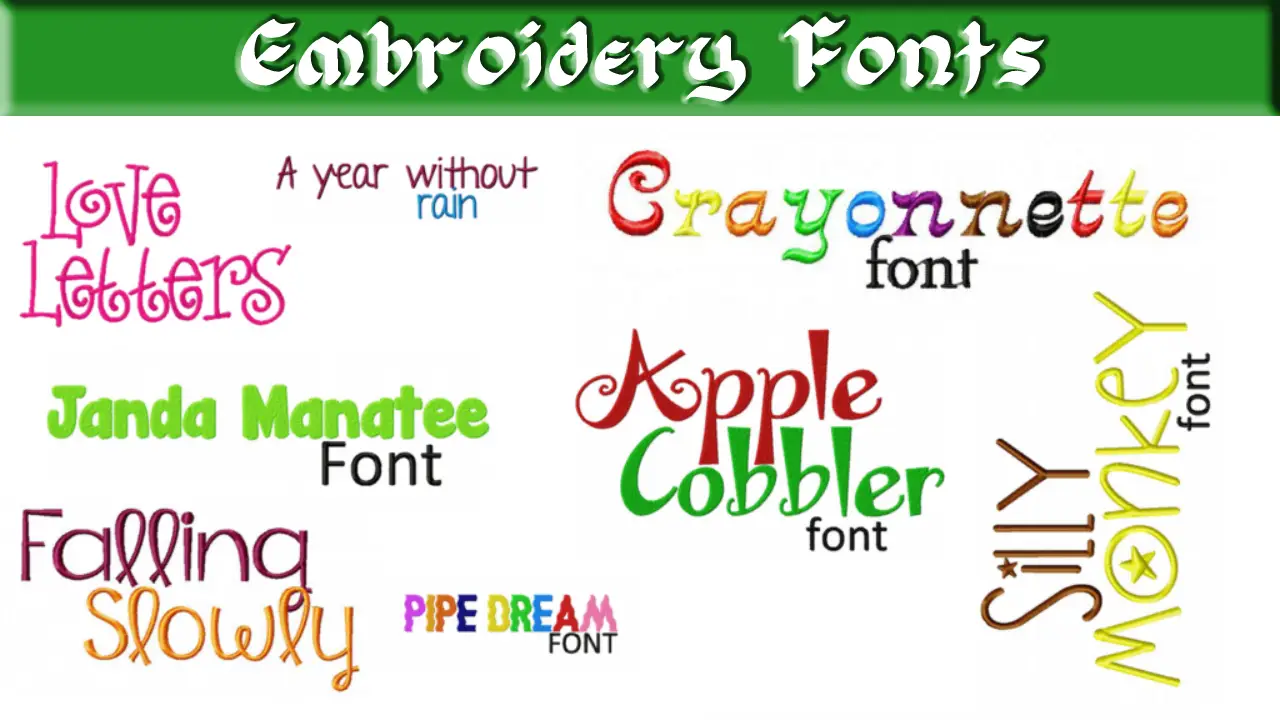
Caratteri da ricamo
Embroidery Fonts
Cosa sono i caratteri di ricamo?
I caratteri di ricamo sono file programmati per creare lettere. Le informazioni contenute nel file sono digitalizzate in modo che la macchina da ricamo possa leggerle. Utilizzando il file, la macchina da ricamo può ricreare le lettere o le parole sul tessuto. Font aggiuntivi possono essere scaricati gratuitamente o acquistati separatamente.What Are Embroidery Fonts?
Un carattere ricamato è molto simile al carattere che usi sul tuo computer o telefono. Il tuo computer potrebbe avere Ariel o Times come font New Roman. Il carattere è uno stile di scrittura.
Le macchine da ricamo hanno una gamma di caratteri o caratteri. La differenza con il carattere specifico del ricamo è che deve essere leggibile dalla macchina da ricamo. Tutte le informazioni necessarie a una macchina da ricamo per riprodurre i caratteri sono memorizzate in un file di ricamo.
Quando si tratta di caratteri ricamati, ci sono tre diversi tipi di file. Let’;Diamo un'occhiata a loro e vediamo quanto sono diversi.
caratteri BX
I caratteri BX consentono principalmente ai digitalizzatori di prendere i caratteri dei loro file di cucito (o ricami) e assegna un colpo (tasto sulla tastiera) a ciascuna lettera in modo che si adattino al programma software proprietario. Facile da digitare.
Molti digitalizzatori hanno utilizzato questo servizio, e ad essere onesti, I think that’;È il problema principale con questo tipo di carattere ricamato. Indipendentemente dalla loro esperienza, chiunque può sviluppare e vendere font BX, che hanno inondato il mercato di caratteri BX digitalizzati male e automatizzati.
Ad essere onesti, molti digitalizzatori fanno un ottimo lavoro nel convertire i loro font in BX, ma allo stesso tempo, il numero di digitalizzatori medi che hanno creato caratteri BX supera di gran lunga i caratteri buoni. Indipendentemente da chi li ha digitalizzati, I caratteri BX sono tutti i tratti definiti dai file di ricamo (o modelli di ricamo).
Mi è stato ripetutamente chiesto se forniamo il formato BX per i nostri font in Embroidery Legacy. Anni fa, Uno sviluppatore mi ha chiesto di convertire il mio lavoro in formato BX. La risposta era sì e ancora no. Non fornisco il formato BX; Il motivo è semplice:
Qualsiasi carattere è buono quanto il digitalizzatore che lo ha creato. Mettere il mio lavoro nel pool di digitalizzatori eccellenti e cattivi non fa più differenza per me e per la qualità con cui abbiamo lavorato così duramente per costruire la nostra reputazione.
I know that the developers of the BX format have recently released a “;replica”; of Wilcom’;s tecnologia di font ESA basata su oggetti di fama mondiale all'interno dei più alti livelli del loro modulo di digitalizzazione del software; ma come ho notato prima Detto questo, qualsiasi carattere è buono come un digitalizzatore.
Carattere di ricamo ESA
Font dell'ESA (Alfabeti specifici per ricamo) sono il tipo più avanzato e personalizzato di caratteri ricamati. I font ESA sono un formato di file di font di ricamo specifico per il software di ricamo Hatch e Wilcom. Questi caratteri della tastiera sono la forma più personalizzabile di carattere ricamo in quanto possono essere facilmente regolati, ridimensionato, e rimodellato, il tutto dandoti risultati professionali.
Ironia della sorte, I font ricamo ESA esistono da molto tempo, and that’;Questo è uno dei motivi per cui Wilcom è da decenni un leader globale nel settore del ricamo commerciale.
Ricordo di aver creato i font ESA 27 anni fa, quando gestivo le mie due fabbriche multitesta dove produciamo più di 10,000,000 prodotti da ricamo ogni anno. Avevo due motivi per creare questi caratteri nei giorni lavorativi.
1. I didn’;t desidera digitalizzare gli stessi caratteri più e più volte (come ho detto prima, diventa molto noioso). Volevo anche assicurarmi che i caratteri che stavo usando soddisfacessero le aspettative degli utenti e me stesso.
1. ESA fonts have the same features as Wilcom’;s Formato EMB. Non solo questo significa che tutte le lettere sono progettate per adattarsi al punto più vicino, but they also include Wilcom’;S incredibili funzionalità Fabric Assist e molto altro ancora.
TTF
File di tipo vero (TTF) i caratteri non sono caratteri di ricamo. Sono stati sviluppati da Apple negli anni '80 per essere utilizzati con i computer. I caratteri sono le lettere che appaiono sullo schermo nella loro forma originale. In altre parole, proprio come li digiti. Indipendentemente dalla risoluzione o dalle dimensioni dello schermo.
Una volta installato nel software di ricamo, il file TTF viene convertito automaticamente nel formato ricamo quando lo usi. Anche se questo cambiamento può essere un po' incostante.